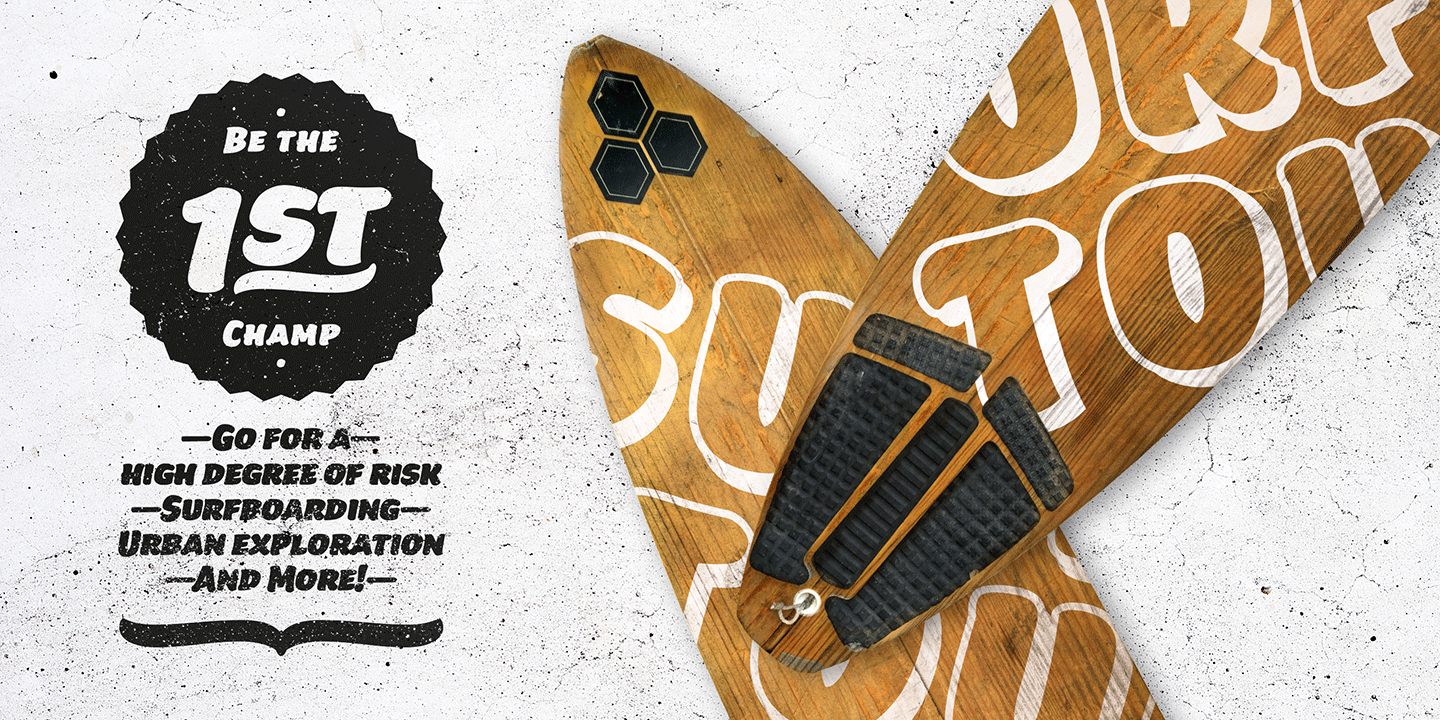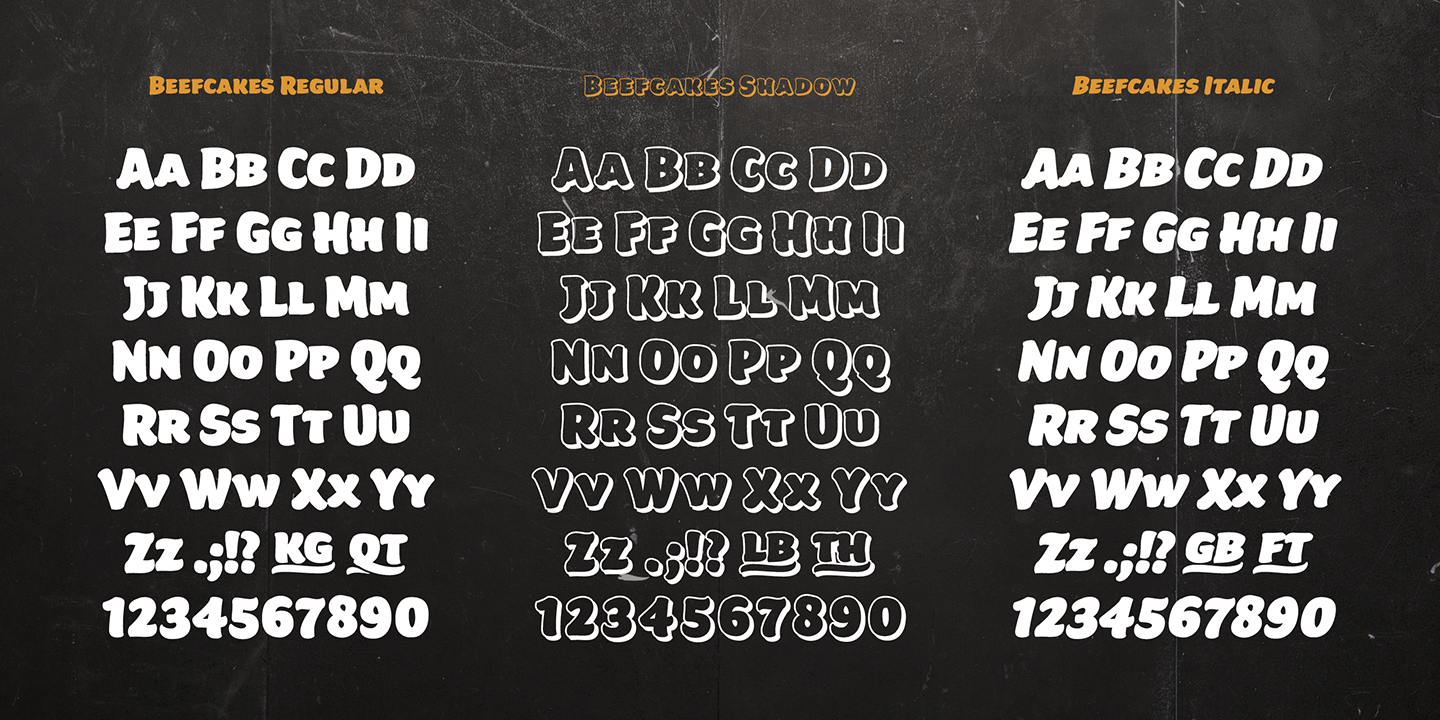
Beefcakes Font
Description de Beefcakes Font
Inspiré de la publicité dans les boucheries et les vitrines des supermarchés, Beefcakes imite le lettrage de style « gros pinceau » – avec une touche contemporaine. Cette conception n’est pas destinée aux typographiquement timides ; il fait une déclaration puissante et conviviale sur papier et à l’écran. Les titres publicitaires, les affiches, les couvertures, les menus et les emballages sont tous dans la timonerie de Beefcakes. Bien qu’il y ait un peu de monde sur les petits écrans, d’importants types de sites Web et de jeux font également partie du kit Beefcakes.